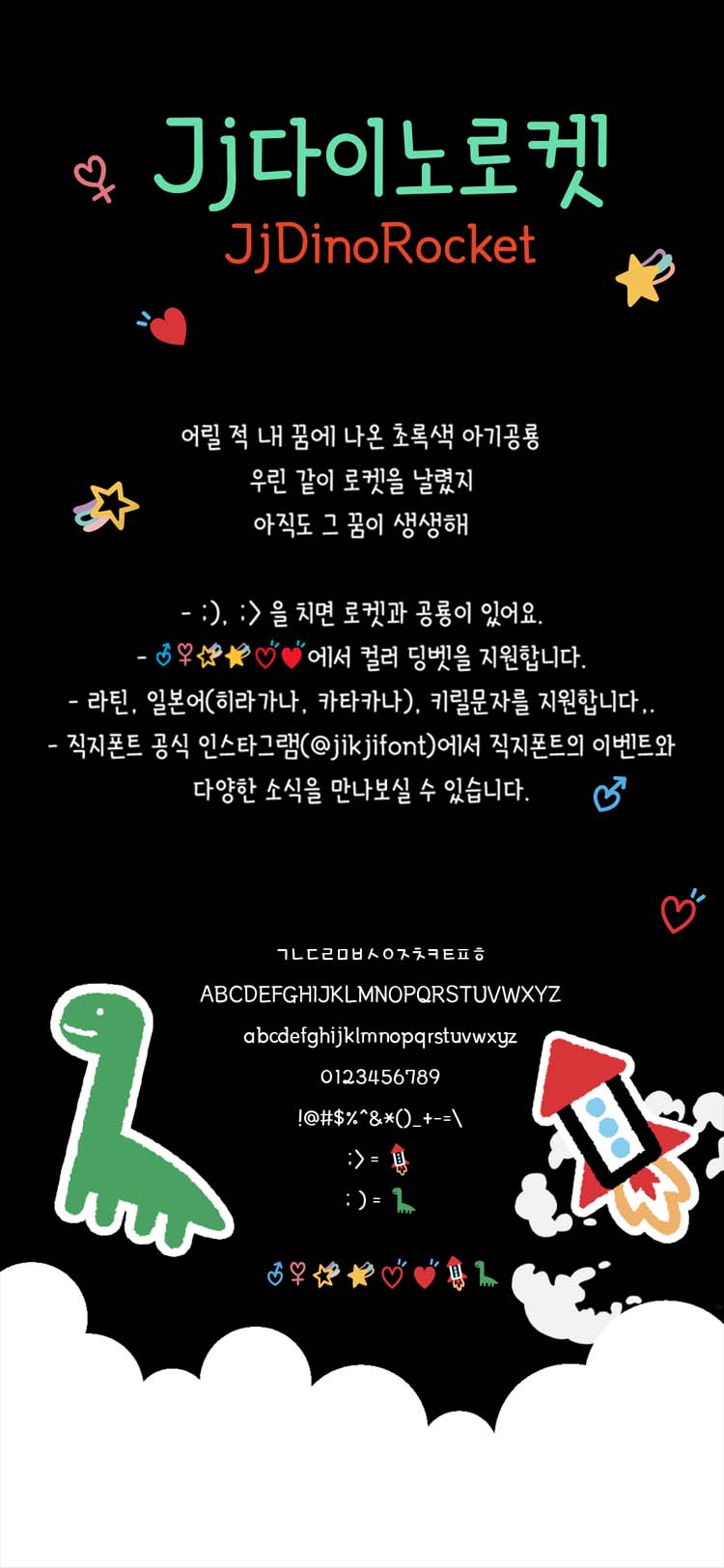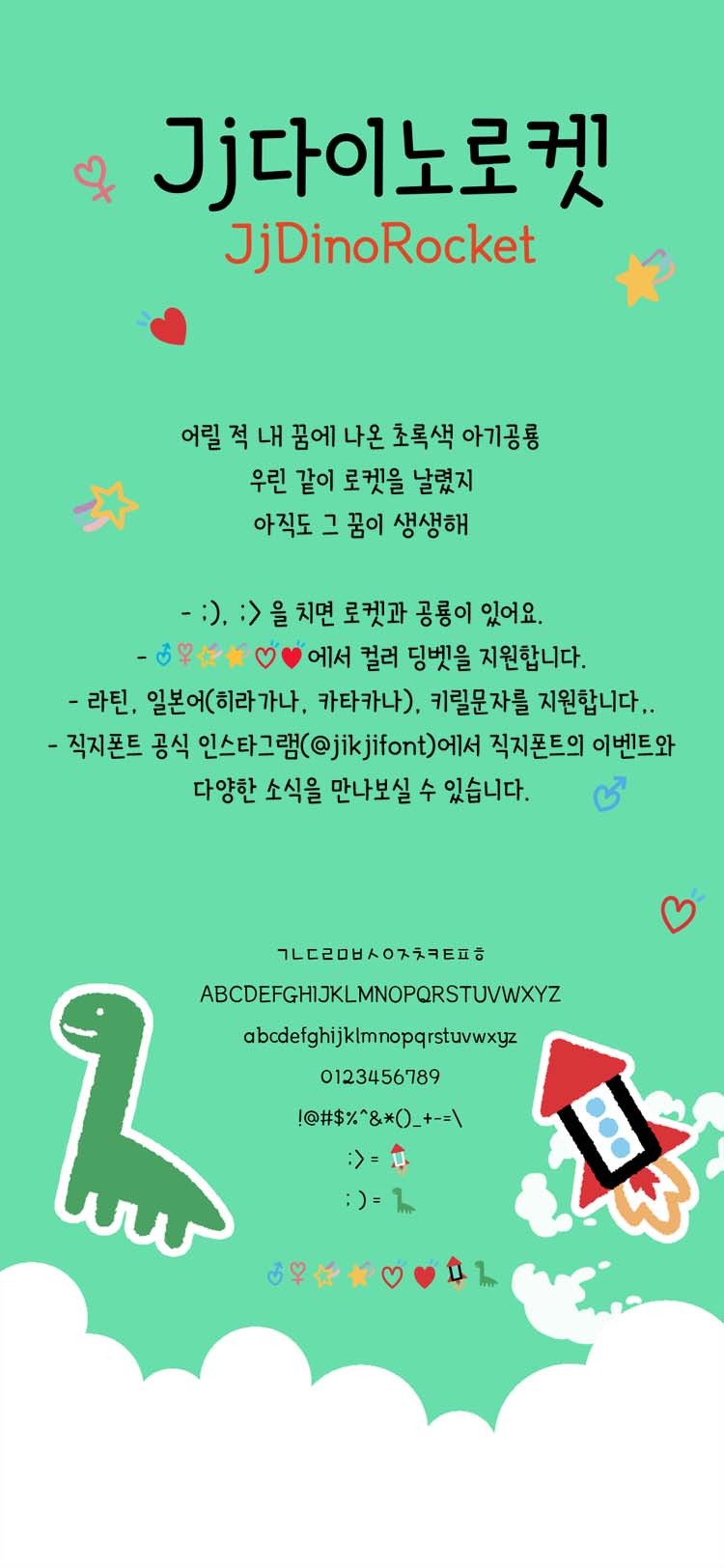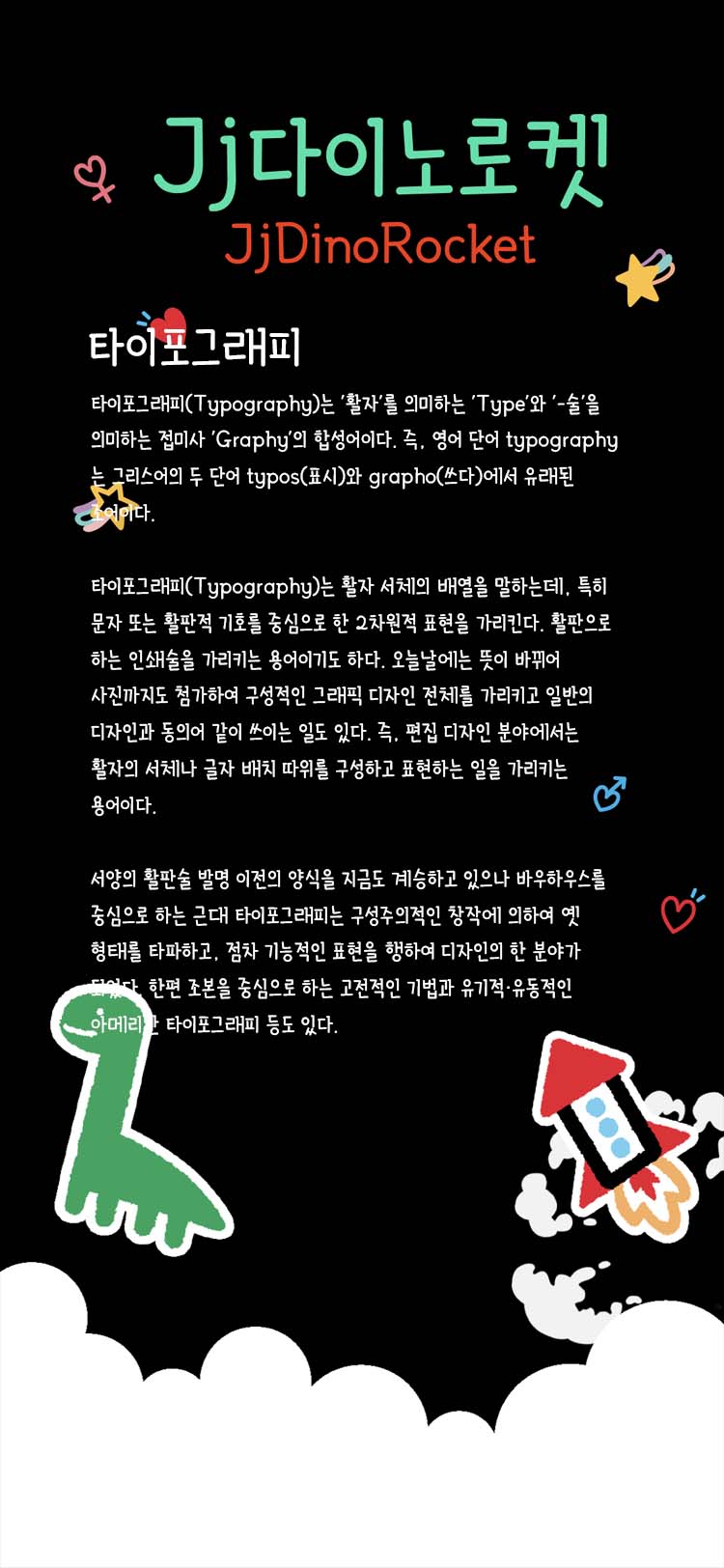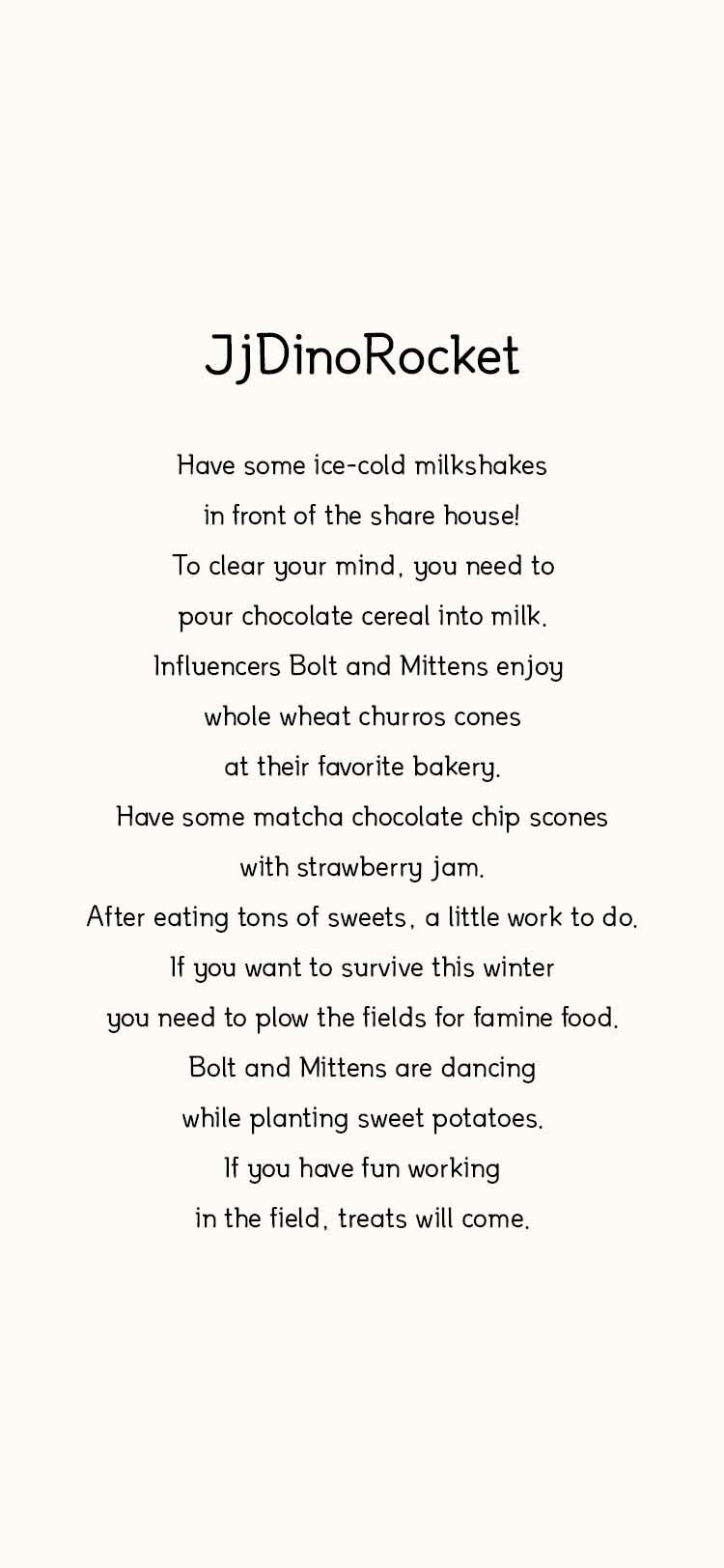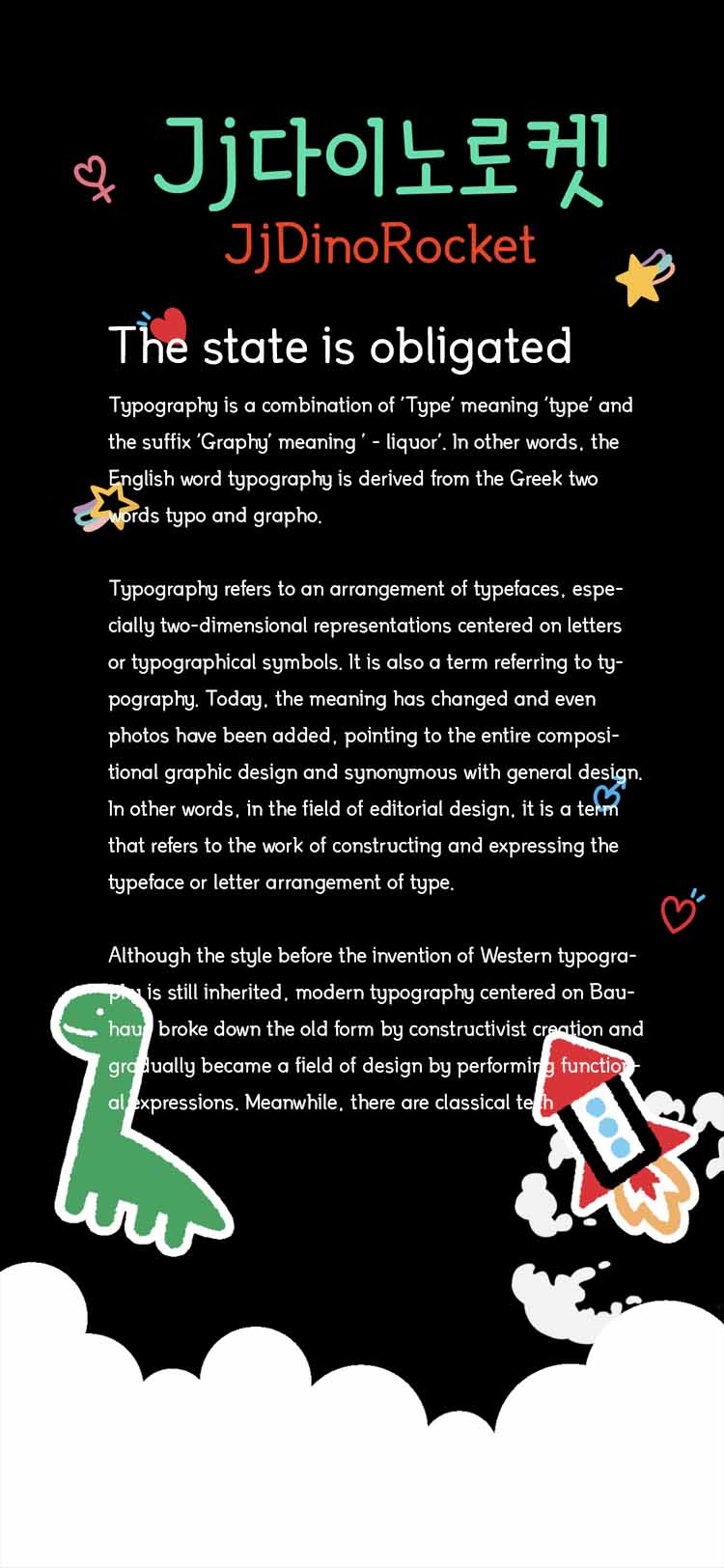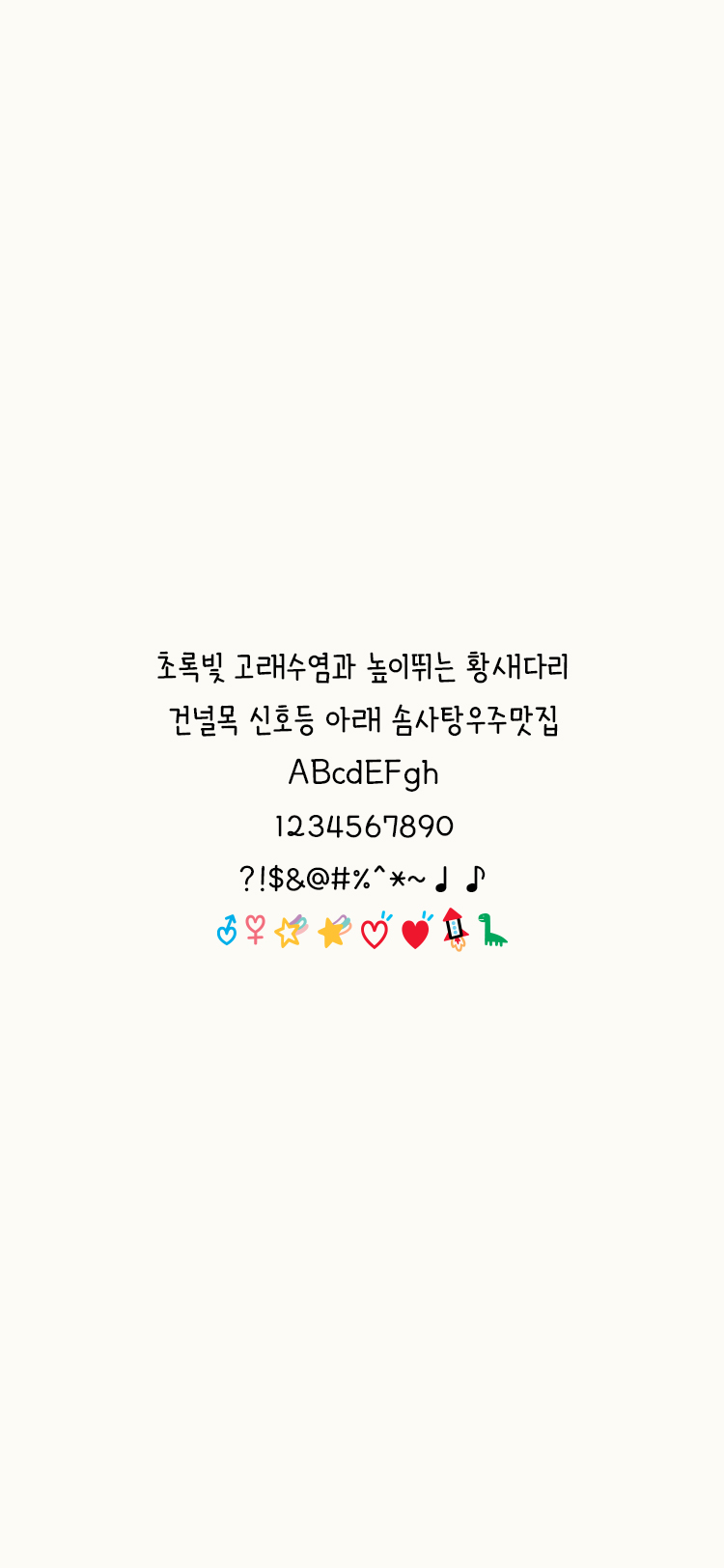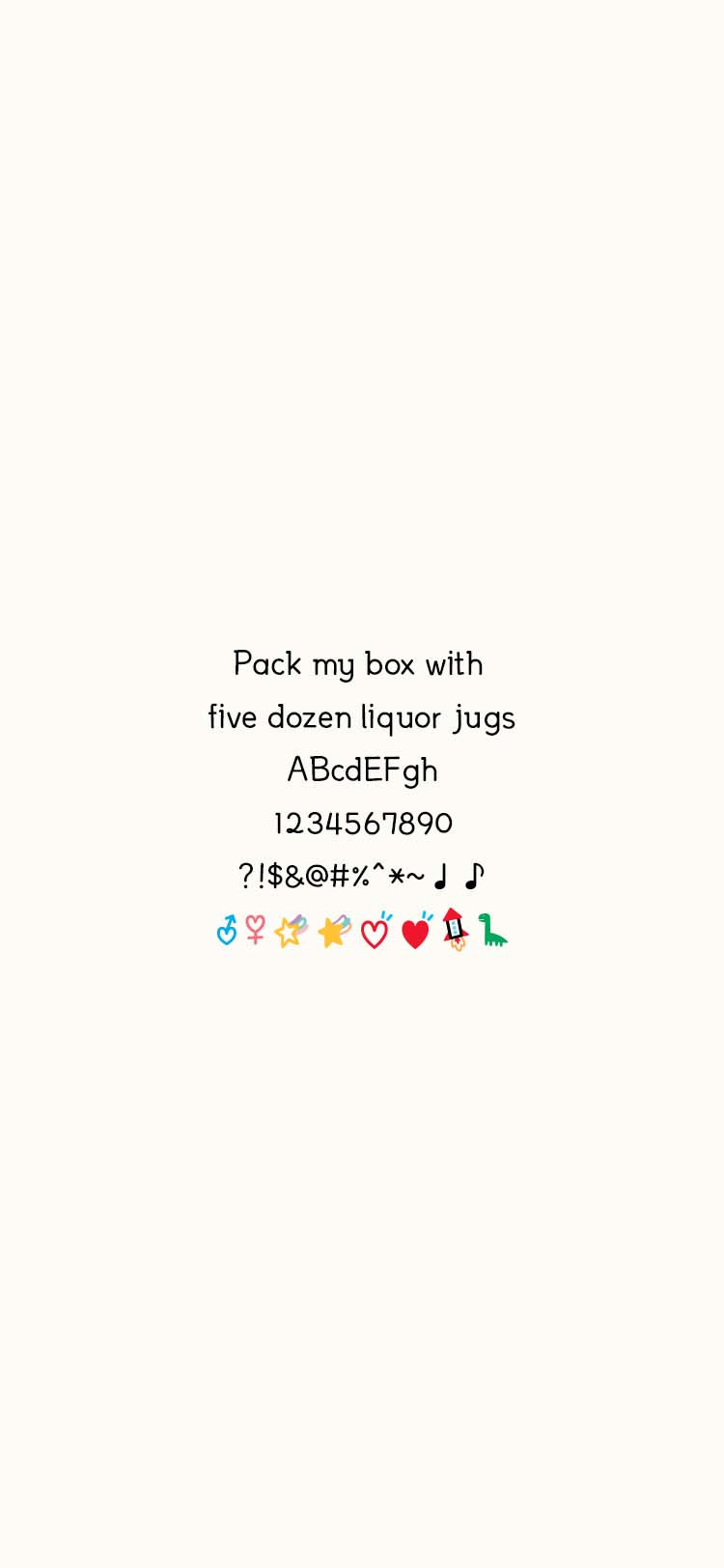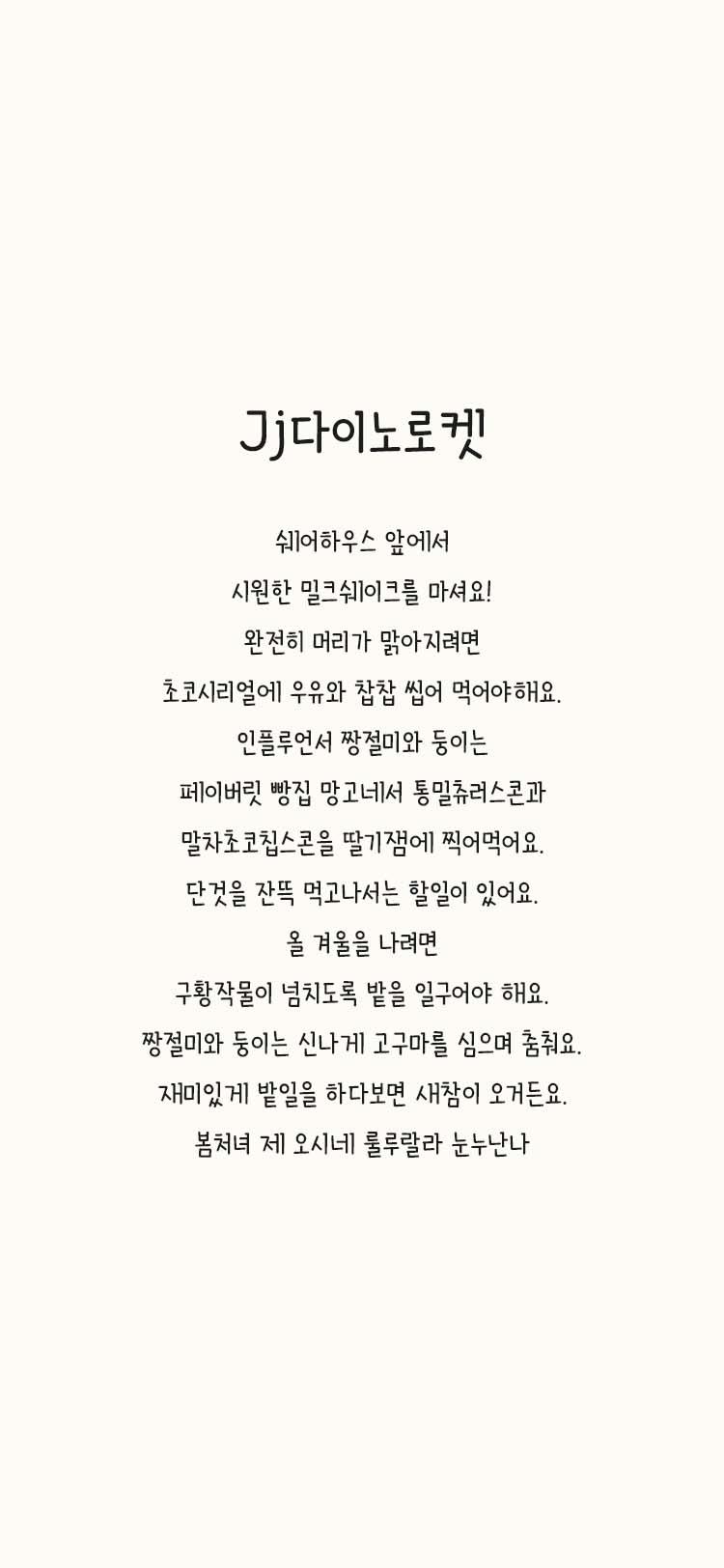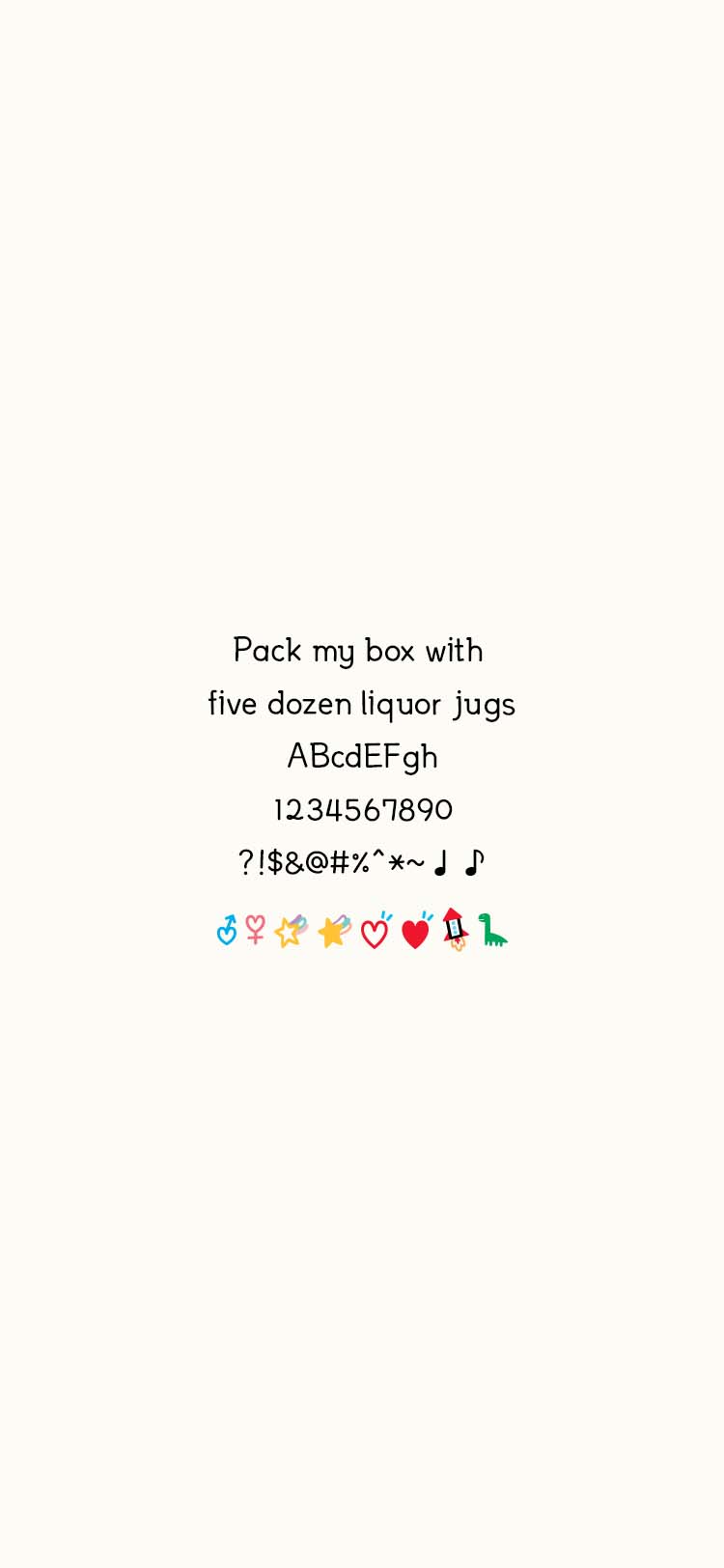
우린 같이 로켓을 날렸지
아직도 그 꿈이 생생해
- ;), ;> 을 치면 로켓과 공룡이 있어요.
- ♂♀☆★♡♥에서 컬러 딩벳을 지원합니다.
- 라틴, 일본어(히라가나, 카타카나), 키릴문자를 지원합니다,.
- 한글 11,172자 / 라틴 95자 / 부호 985자
- Jj다이노로켓 / JjDinoRocket